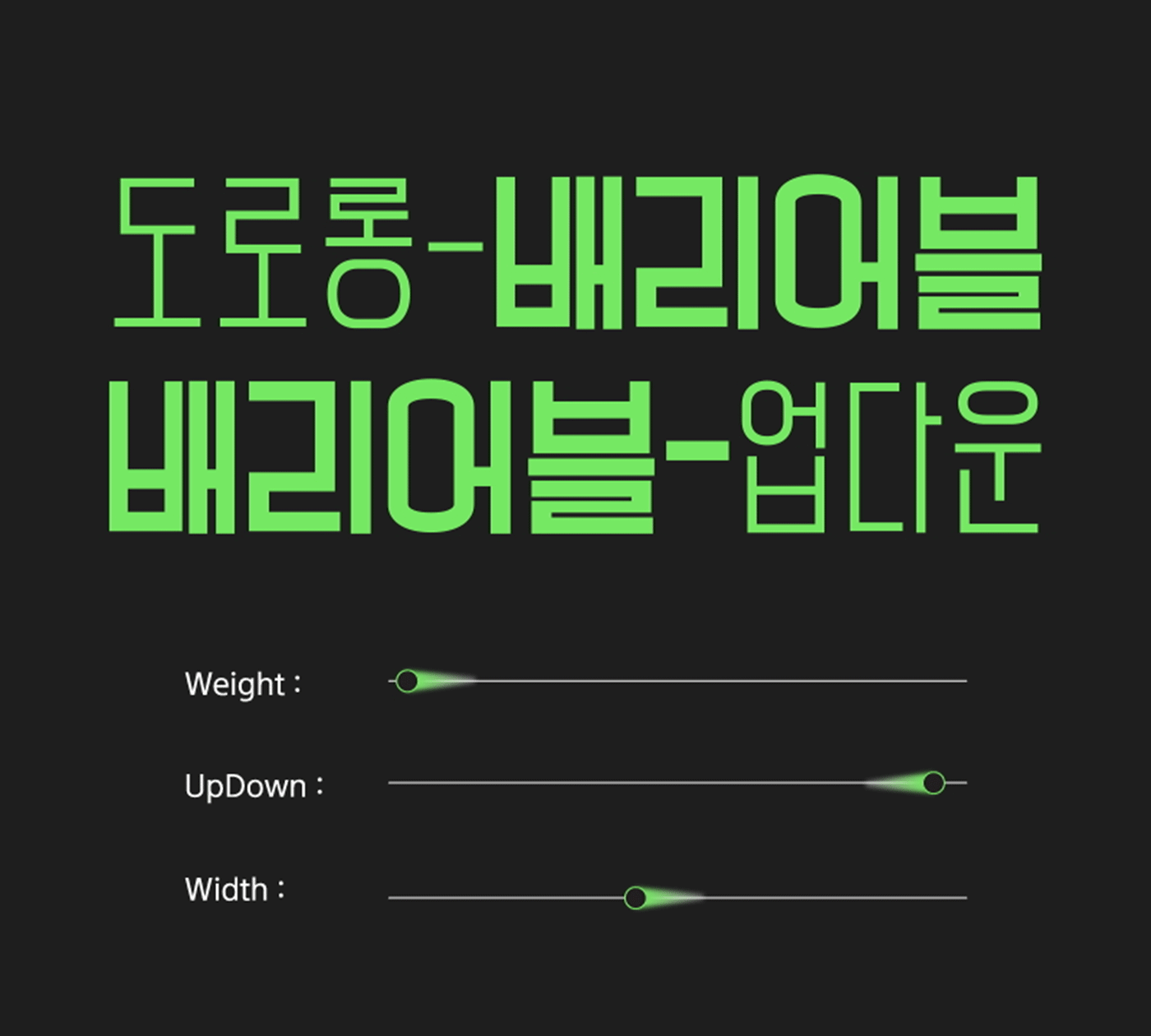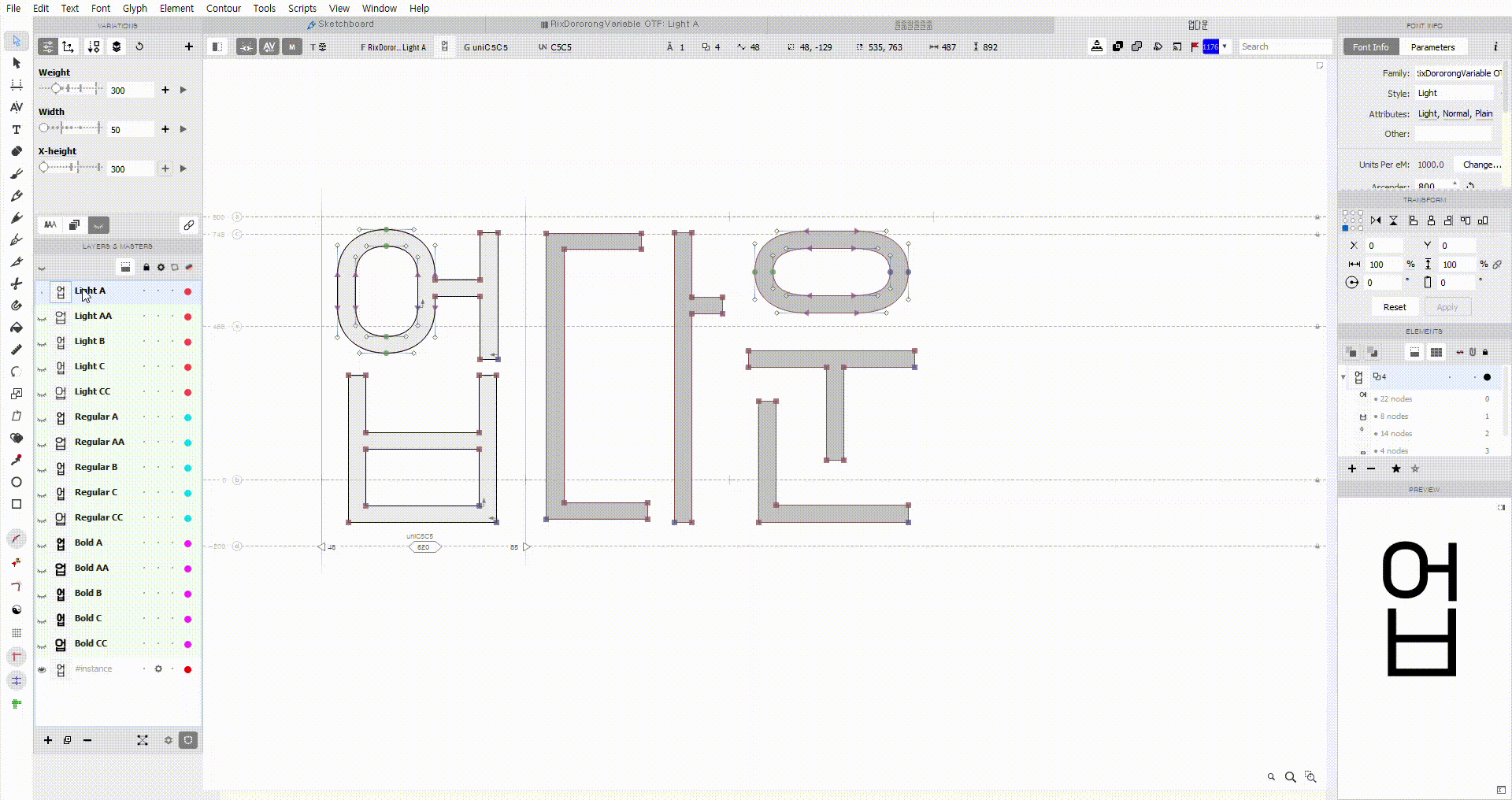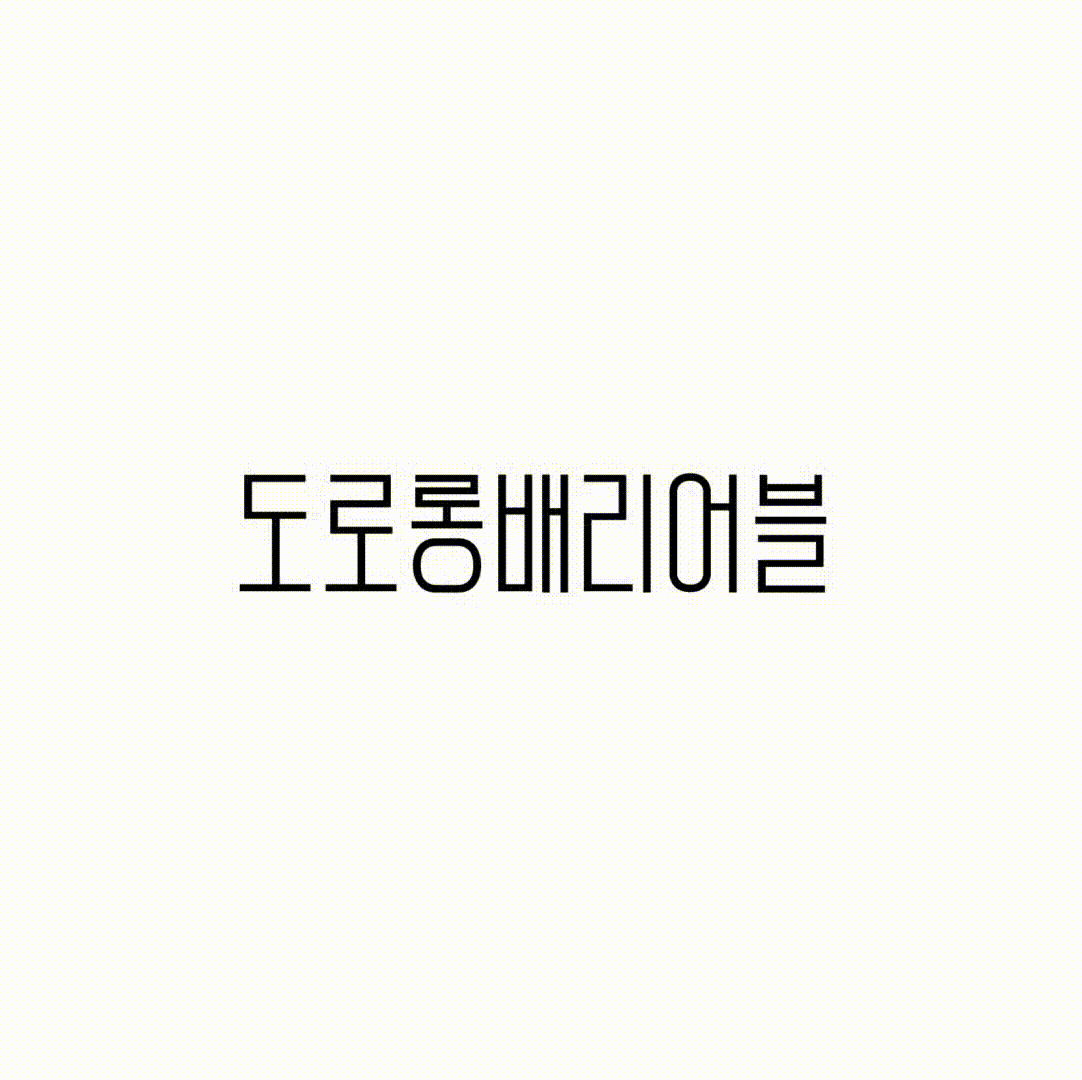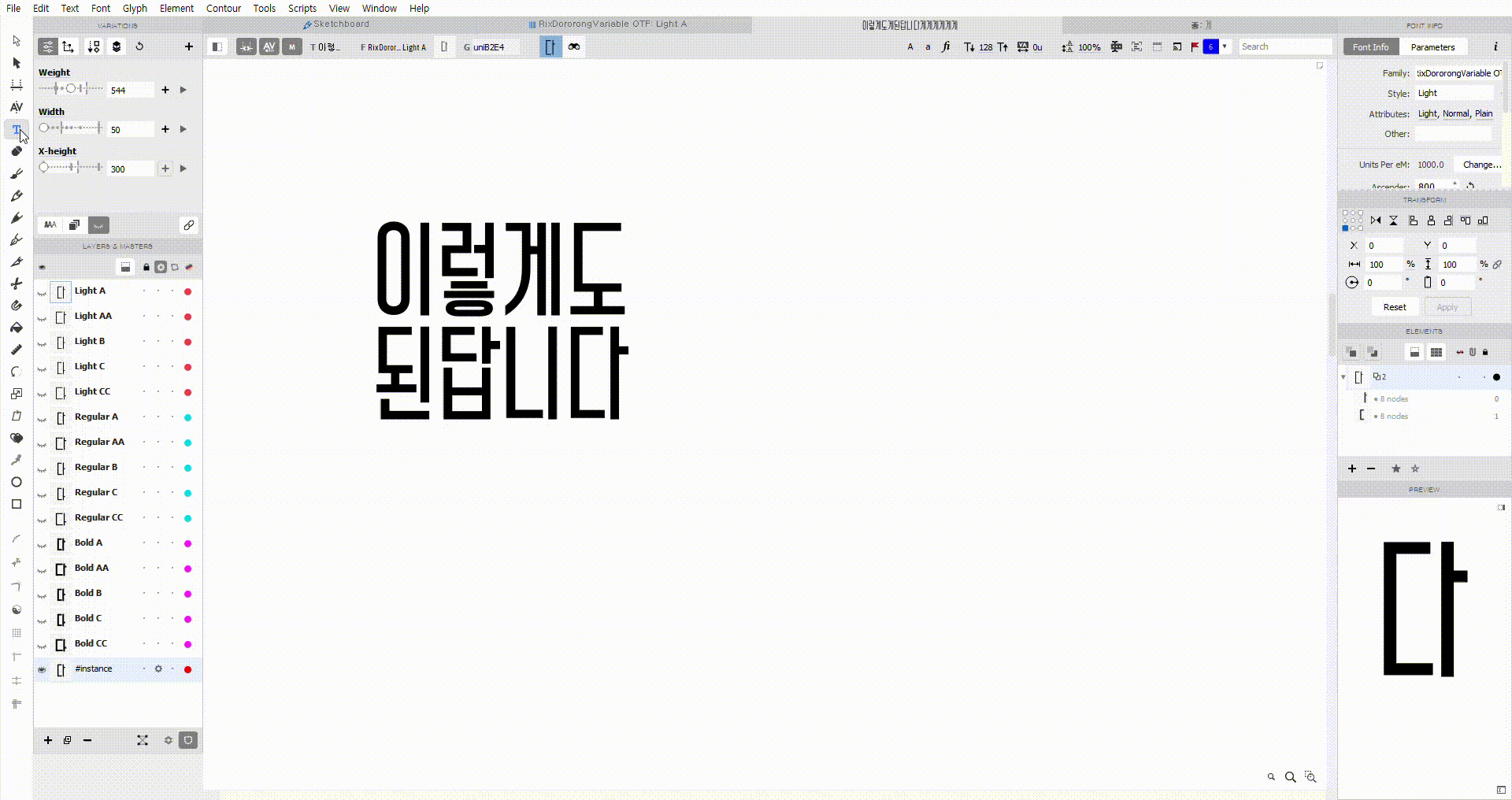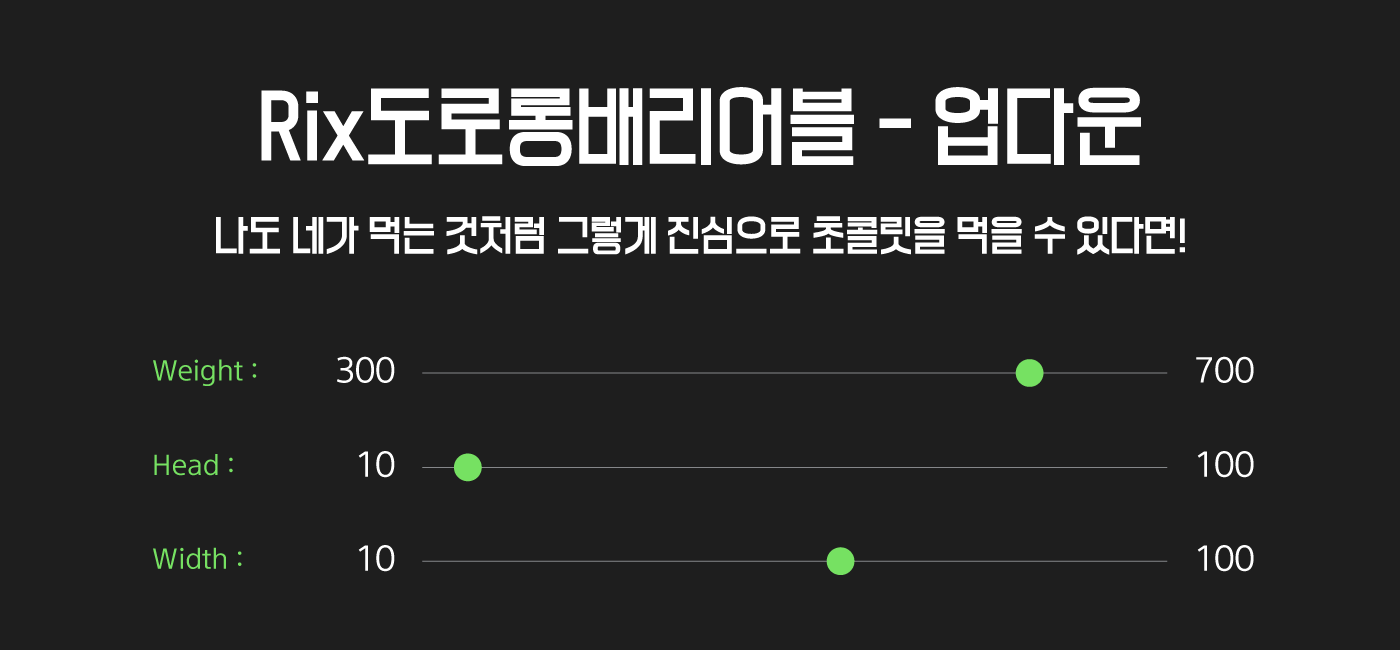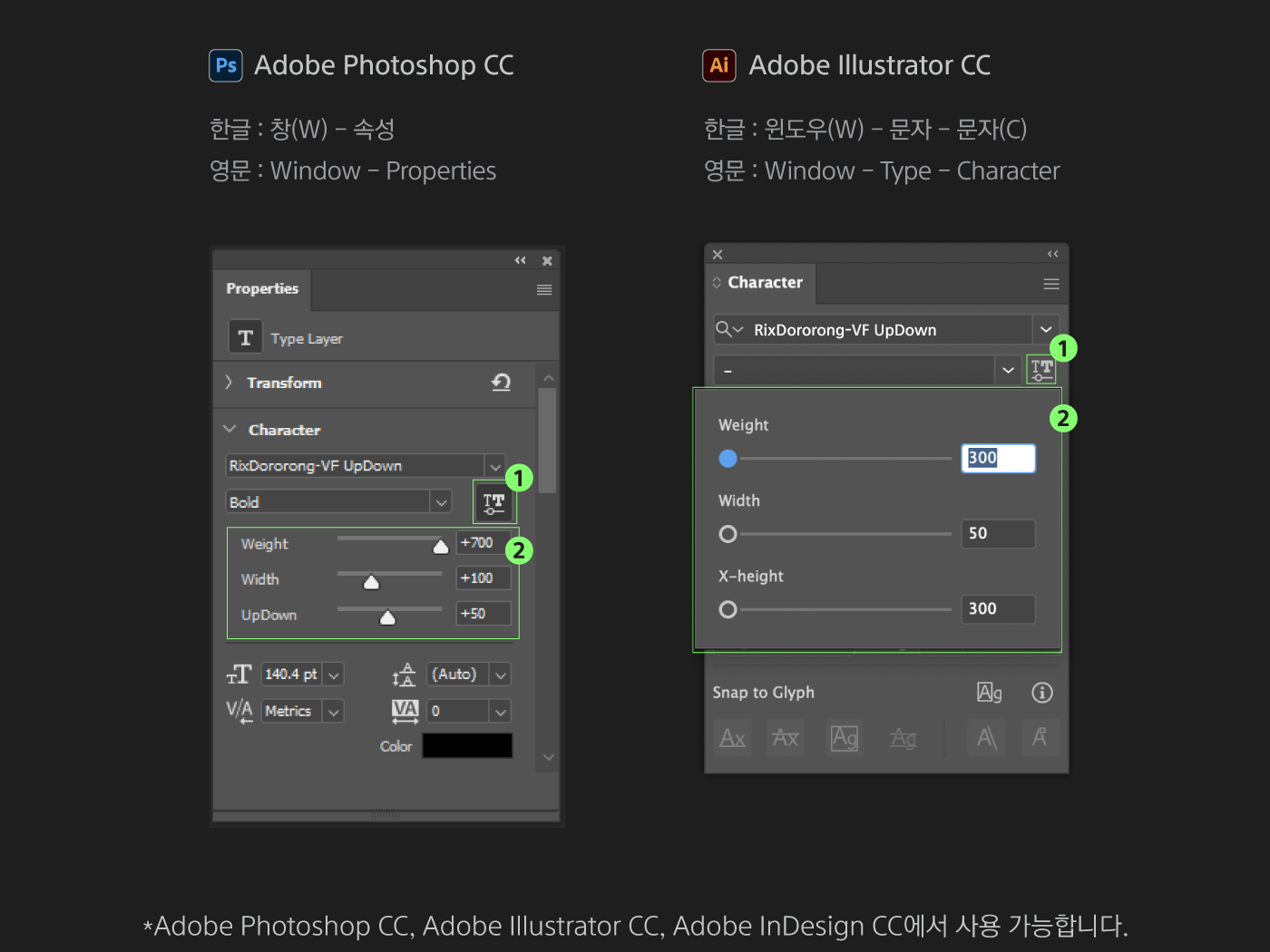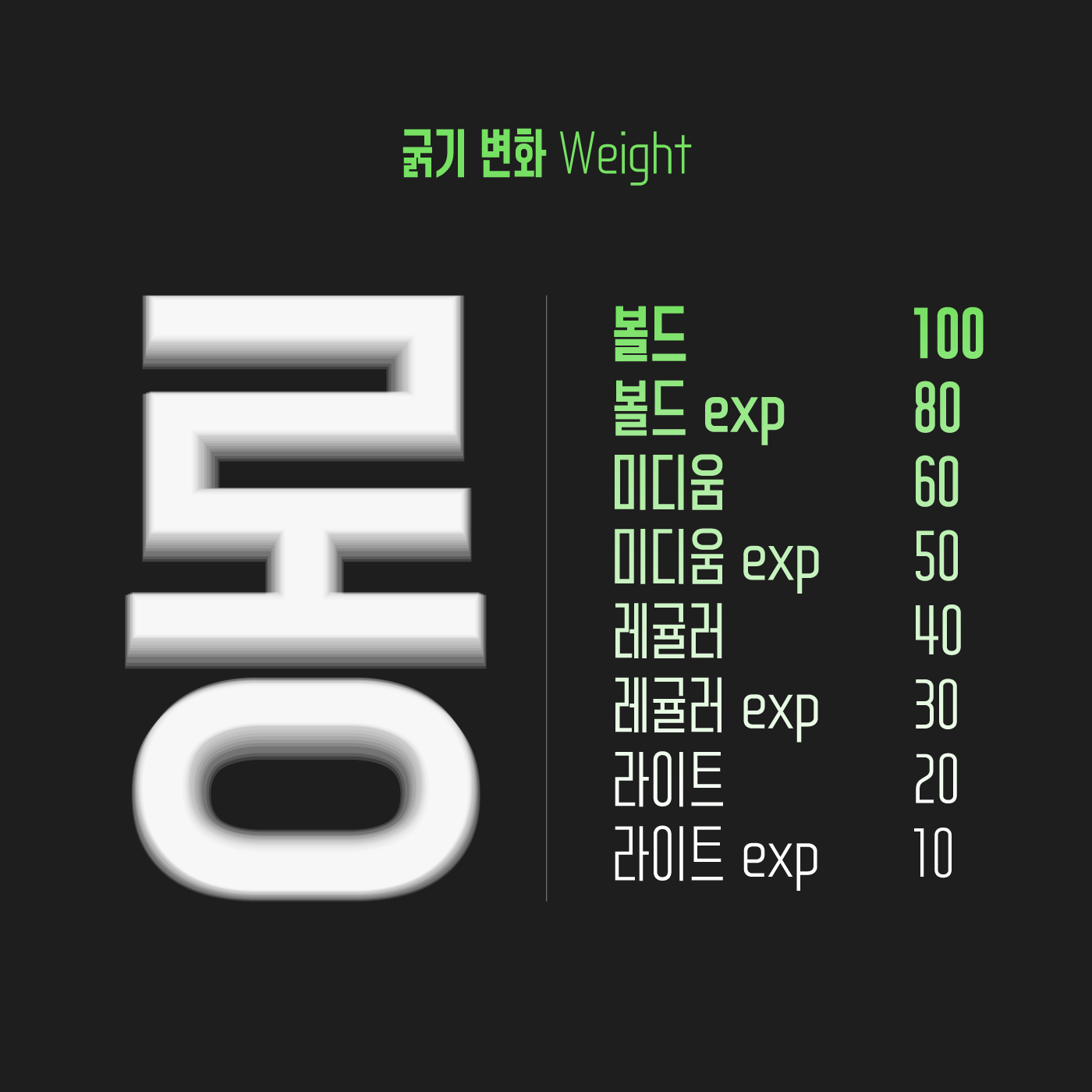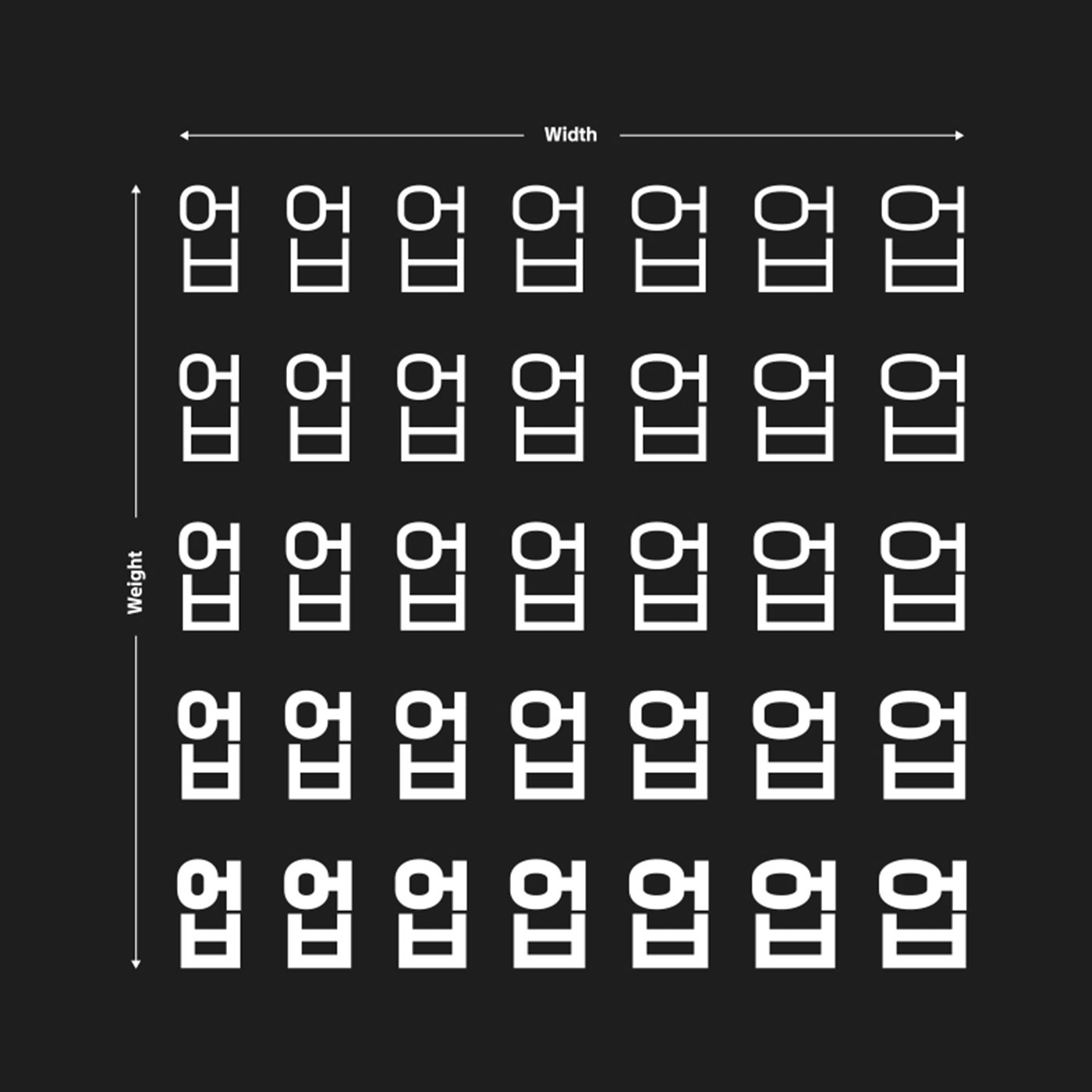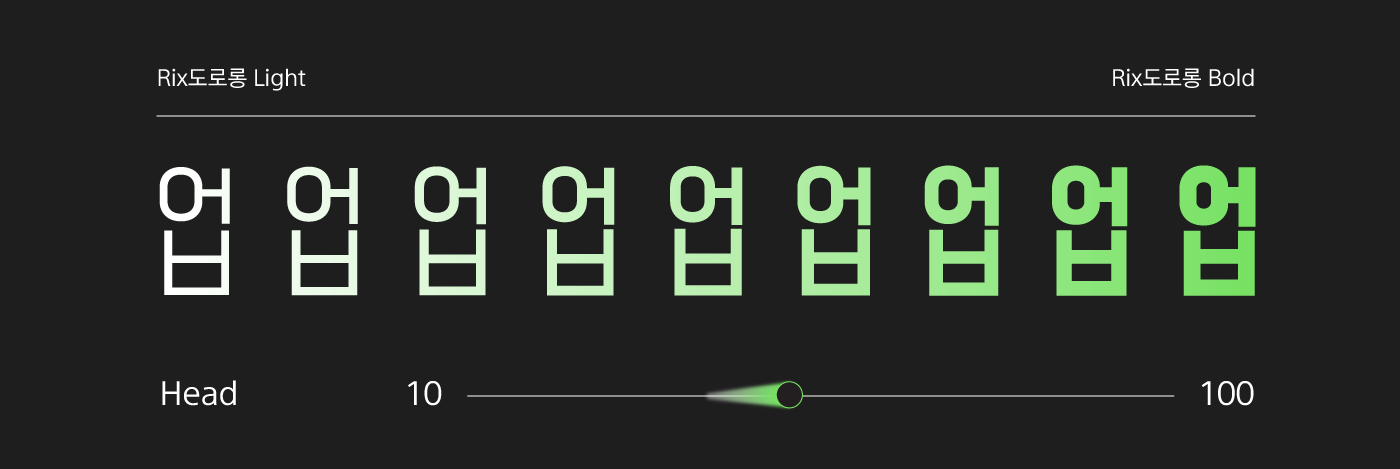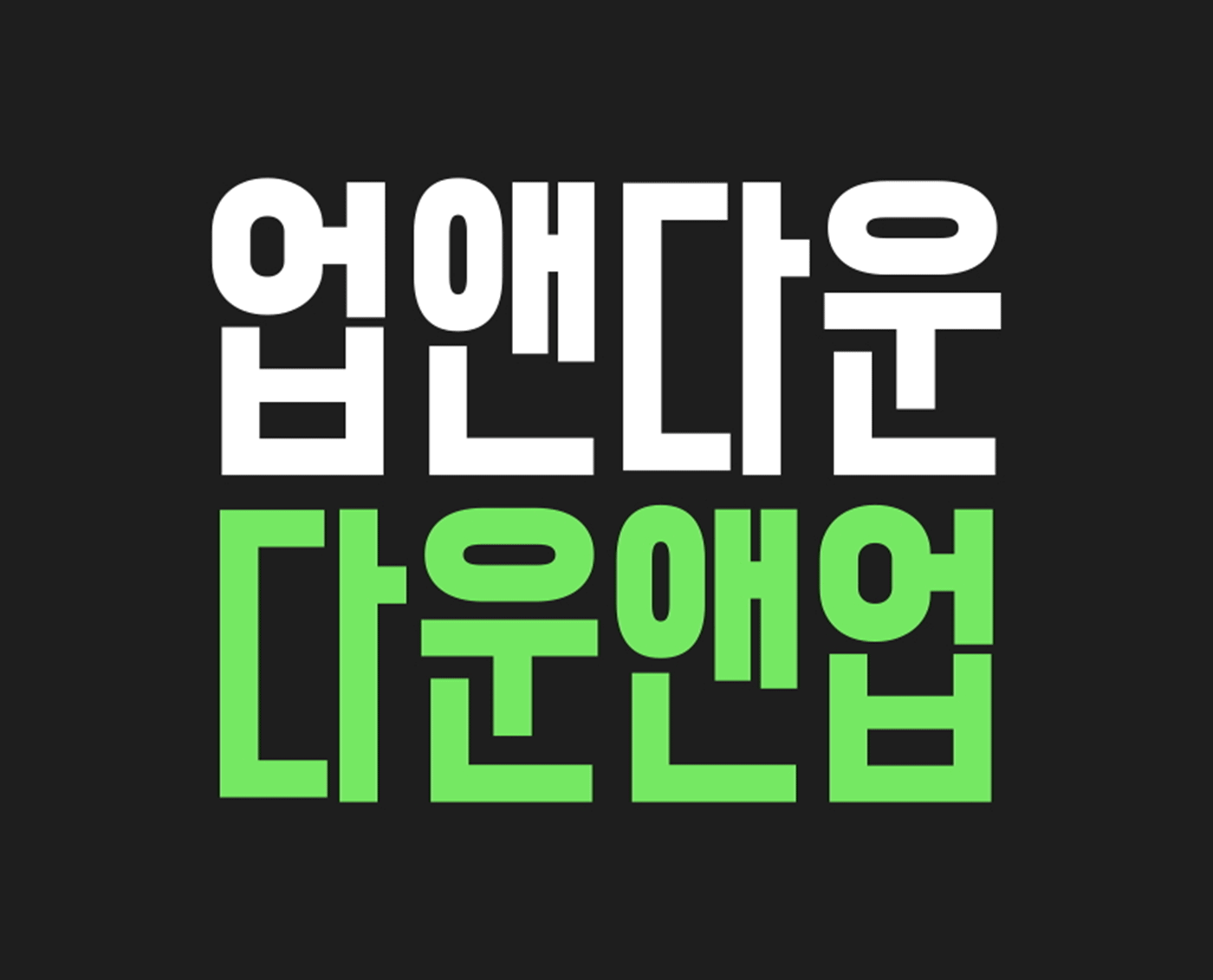
안녕하세요. 오늘은 뜨거워진 날씨만큼 핫♨️하게 찾아온 8월의 신서체「Rix도로롱-VF UpDown」을 소개합니다! 제목용 서체이지만 얇은 거 두꺼운 거 다 되는 활용도 높은 장체 스타일의 글꼴 Rix도로롱을 기억하시나요? 이번 신규 폰트는 이 도로롱체를 기반으로 제작한 첫 번째 배리어블 폰트로 사용자가 직접 글자의 속성을 조절하여 사용할 수 있는 서체입니다. Rix도로롱 시리즈의 창시자(!) 유현주 디자이너와의 인터뷰를 통해 폰트에 대해 더 자세히 알아볼게요 :)
안녕하세요. 소개 부탁드립니다! 안녕하세요. 작년 Rix도로롱을 출시하고 그 시리즈인 Rix도로롱슬랩을 출시했습니다. 이번에는 (아마도?) 마지막 도로롱 시리즈인 Rix도로롱배리어블로 돌아온 유현주입니다.
전에 인터뷰에서 말씀하신 배리어블 폰트가 드디어 출시되었네요! 어떤 과정이 있었나요? 도로롱이 좁은 자폭이 특징인 장체이다 보니 ‘폭을 조정하거나 무게 중심을 조금 바꾸는 변형을 해보면 어떨까?’하는 생각에서부터 시작했습니다. 처음 기획 무렵 Rix락배리어블이 아시아 디자인 프라이즈, 레드닷, iF 디자인 어워드 같은 공모전에서 수상하면서 배리어블 폰트에 관심이 생겼습니다. 이런저런 변형을 하는 김에 배리어블로 만들게 되면 좀 더 재미있는 작업이 되지 않을까 해서 이렇게 출시하게 되었습니다.
워낙 제작도 오래 걸리고 어려운 배리어블 서체라 우여곡절도 있었을 것 같아요. 비하인드를 살짝 말씀해 주신다면? 배리어블 폰트를 만들려면 원도 상에서 점의 속성이나 개수가 모두 동일해야 하고, 축의 양 극단 형태를 모두 작업해야 하는데요, 아무래도 도로롱배리어블은 축의 속성이 굵기, 자폭, 무게중심(UpDown)으로 세 개다 보니 작업할 양이 굉장히 정말 정말 많아지더라고요..? 울면서 작업했습니다. (웃음)
이 폰트를 꼭 써봐야 하는 이유! 최근 TV 방송과 유튜브 영상에서 기존 Rix도로롱이 자막용으로 쓰이는 걸 종종 봤는데, 배리어블 폰트라는 속성을 활용하면 사용자가 직접 더욱 재미있는 효과를 연출할 수 있습니다.
도로롱배리어블 UpDown, 어떻게 사용하면 잘했다고 소문날까요? 우선 기본 형태가 Rix도로롱과 동일하기 때문에 자막이나 제목용에 적합할 것 같고, 배리어블 효과를 좀 더 재밌게 활용한 Gif, 영상이나 무빙 포스터 작업에 사용하셔도 재미있을 것 같습니다!
도로롱배리어블 다른 버전도 준비 중이신 걸로 들었어요. 이번 8월에 출시하는 Rix도로롱배리어블-UpDown은 자폭, 무게 중심이 한 방향으로 동일하게 움직입니다. 9월에 출시될 ZigZag는 속성이 UpDown과 동일하지만 이름에 맞게 조금 더 재미있는 변화를 줄 예정입니다😊
장체 스타일의 심플하고 모던한 서체 Rix도로롱을 기반으로 Weight(두께), Head(무게 중심), 그리고 Width(너비) 세 가지 축으로 구분하여 디자인했습니다. 각 축을 사용자가 이동함에 따라 폰트의 굵기와 무게 중심, 폭이 달라집니다.
글자의 두께는 Light부터 Bold까지 무수히 많은 굵기를 세밀하게 표현할 수 있습니다. 너비 또한 아주 좁은 형태부터 넓게 조절할 수 있어 글자의 스타일와 분위기에 다양한 변주를 줄 수 있습니다.
무게 중심을 Up & Down
Rix도로롱배리어블 UpDown은 글자의 무게 중심을 위, 아래로 이동할 수 있습니다. 기본적으로 Rix도로롱은 좁은 폭을 가지고 처음 출시되었는데요. 배리어블 폰트로 재창조되면서 한정적이었던 글자 폭을 더 늘려서 사용할 수도 있고, 무게 중심을 통해 새로운 이미지도 구현할 수 있게 되었습니다.
모던하고 심플한 디자인의 도로롱배리어블은 글자 무게 중심의 이동이나 굵기, 너비의 차별화로 다양한 작업에 재미있게 활용할 수 있습니다.
도로롱배리어블 UpDown은 심플하고 모던한 디자인으로 깔끔하고 미래적인 디자인과 잘 어울려요👀 한글 디자인을 기반으로 한 영문, 숫자와도 조화롭게 어우러집니다.
어디에나 잘 어우러질 수 있는 서체 스타일이기 때문에 포스터, 웹페이지, 영상 자막 등에 활용하기 좋습니다. 폰트를 원하는 대로 배리어블하여 제목과 본문 구분 없이 사용할 수 있습니다.
오늘 이렇게 8월의 신규 폰트 Rix도로롱배리어블-UpDown을 만나봤는데요. 공간을 자유롭게 움직일 수 있는 도로롱배리어블과 함께 재미있고 다양한 콘텐츠를 많이 만나게 되면 좋겠습니다! 그럼 다음 달에는 도로롱배리어블 2탄 ZigZag로 찾아오겠습니다 :)